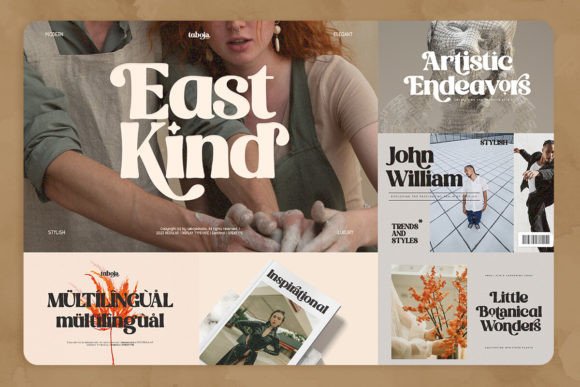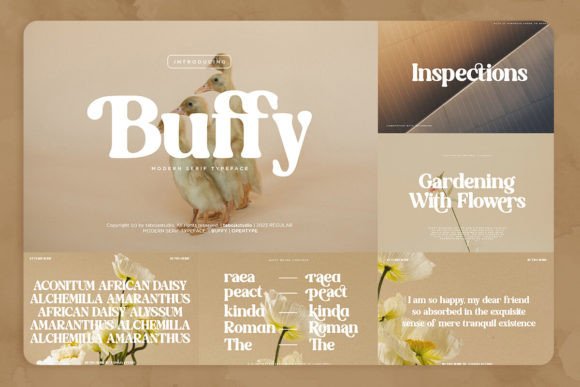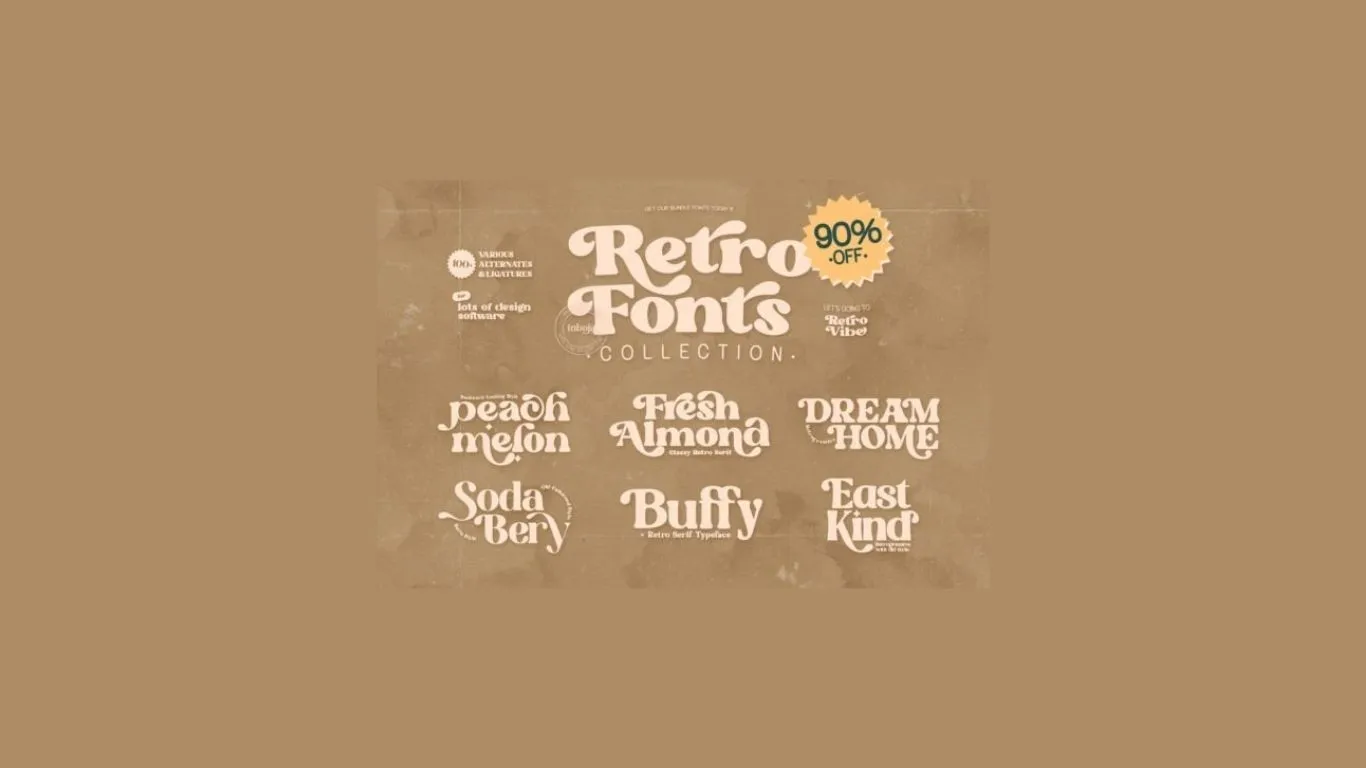
復古英文字體
字型介紹
Retro Fonts Collection 這套字體合集整合了 6 款復古風格字型,平台評分 5.0 分 (滿分),累計超過 2800 人加入收藏,原價 $28 美元。屬於 Serif (襯線體) 系列,融合了復古、優雅與手寫質感,6 款字型分別為:
Fresh Almond Font
Peach Melon Font
Dream Home Font
Buffy Font
Sodabery Font
East Kind Font
適合哪種設計?
Logo 設計:復古感給品牌帶來獨特個性
社群媒體貼文 (Instagram、Facebook 封面圖等)
海報與雜誌排版
T 恤印刷、Print on Demand (POD) 商品設計
部落格標題與網站視覺